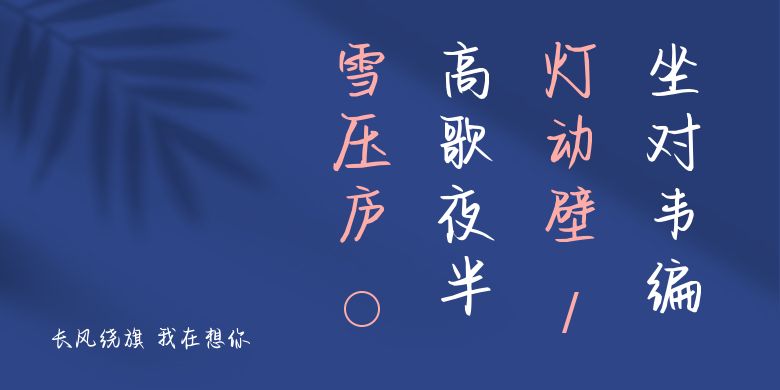
长风绕旗 我在想你
长风绕旗 我在想你,这款字体结构工整、笔画清晰,兼顾美观与易读性,适用于标题、正文、海报、包装、LOGO 等多种场景。字形优雅稳定,风格百搭耐看,适配日常排版与创意设计,让文字呈现更舒适、更具质感。长风绕旗 我在想你一笔一画,皆是细节,以均衡的比例、流畅的线条打造舒适视觉体验,字形端正大气,风格简约现代。无论是商业设计、品牌宣传还是日常排版,都能轻松驾驭,让文字更有格调与力量。长风绕旗 我在想你字体下载。